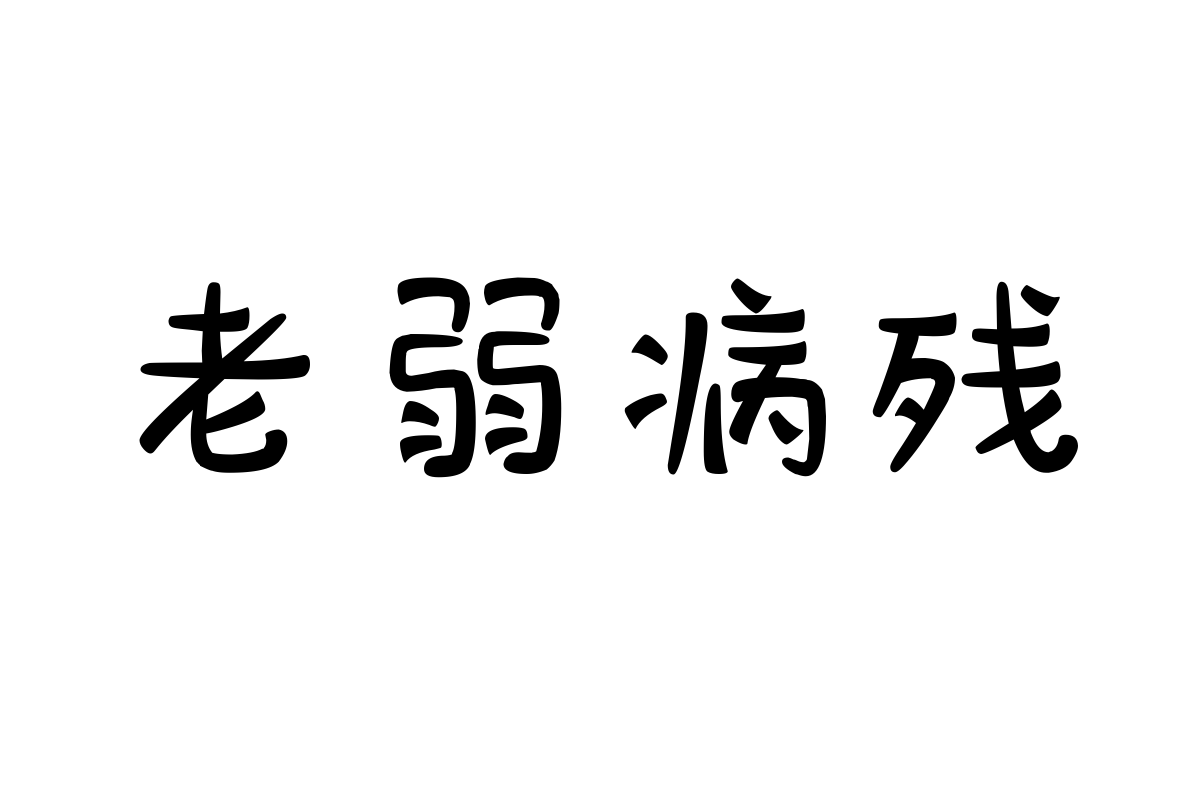
也字工厂维尼体字体是一款具有独特风格的中文字体,由设计师们精心打造。这款字体以其独特的字形结构、流畅的笔画线条和丰富的表现力而受到广大用户的喜爱。
1. 字形结构:也字工厂维尼体字体采用了传统的汉字书写规则,将每个字符的结构进行优化,使其更加符合现代人的审美需求。同时,该字体还融入了一些现代元素,使得整体风格更加时尚。
2. 笔画线条:该字体的笔画线条流畅自然,没有过多的装饰性细节,给人一种简洁、清爽的感觉。这种线条处理方式使得字体在视觉上更加易于识别和阅读。
3. 表现力:也字工厂维尼体字体具有较强的表现力,能够很好地传达出文字所要表达的情感和意境。无论是用于广告设计、海报制作还是其他需要强调文字效果的场景,都能展现出其独特的魅力。
4. 适用范围:也字工厂维尼体字体适用于多种应用场景,如网页设计、平面设计、包装设计等。它不仅适用于商业用途,也适合个人使用,为人们提供丰富的字体选择。
总之,也字工厂维尼体字体是一款具有独特风格的中文字体,它以其流畅的笔画线条、简约的设计和强大的表现力赢得了广大用户的喜爱。无论是用于商业还是个人用途,都能找到适合自己的应用场景。